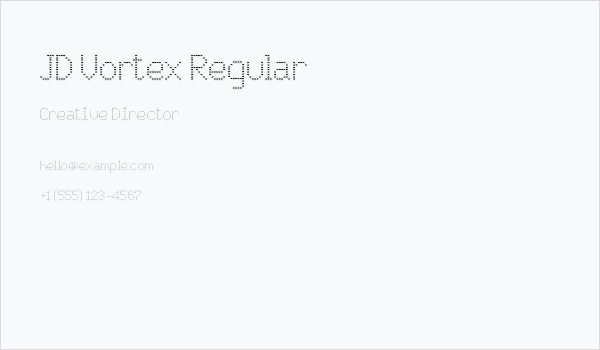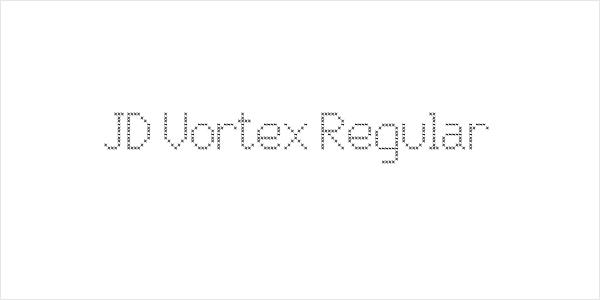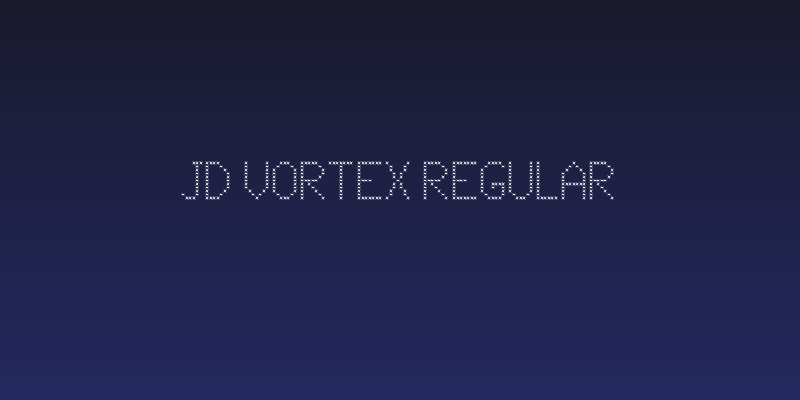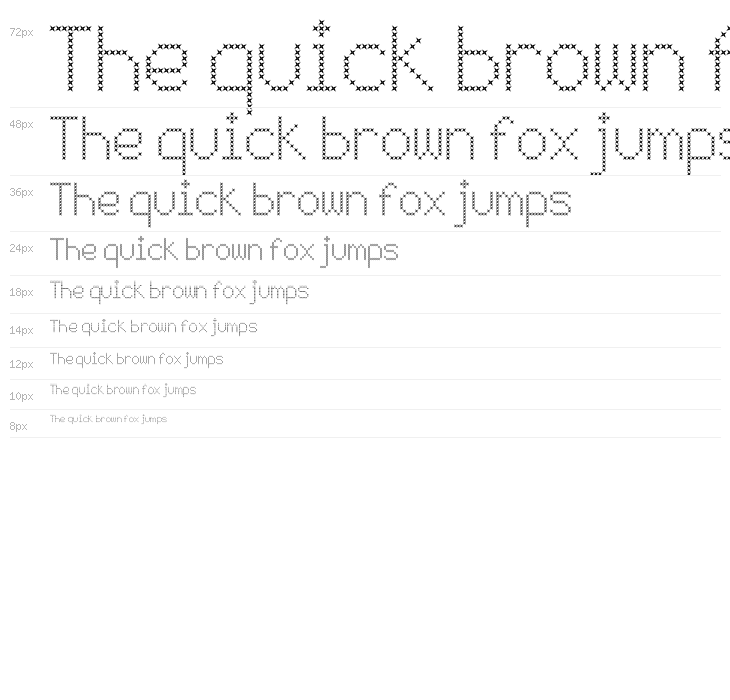
JD Vortex Regular Font
Fonts by Jecko Development
| Projets proposés | Ideal for creative projects such as greeting cards, posters, children's books, and playful branding. |